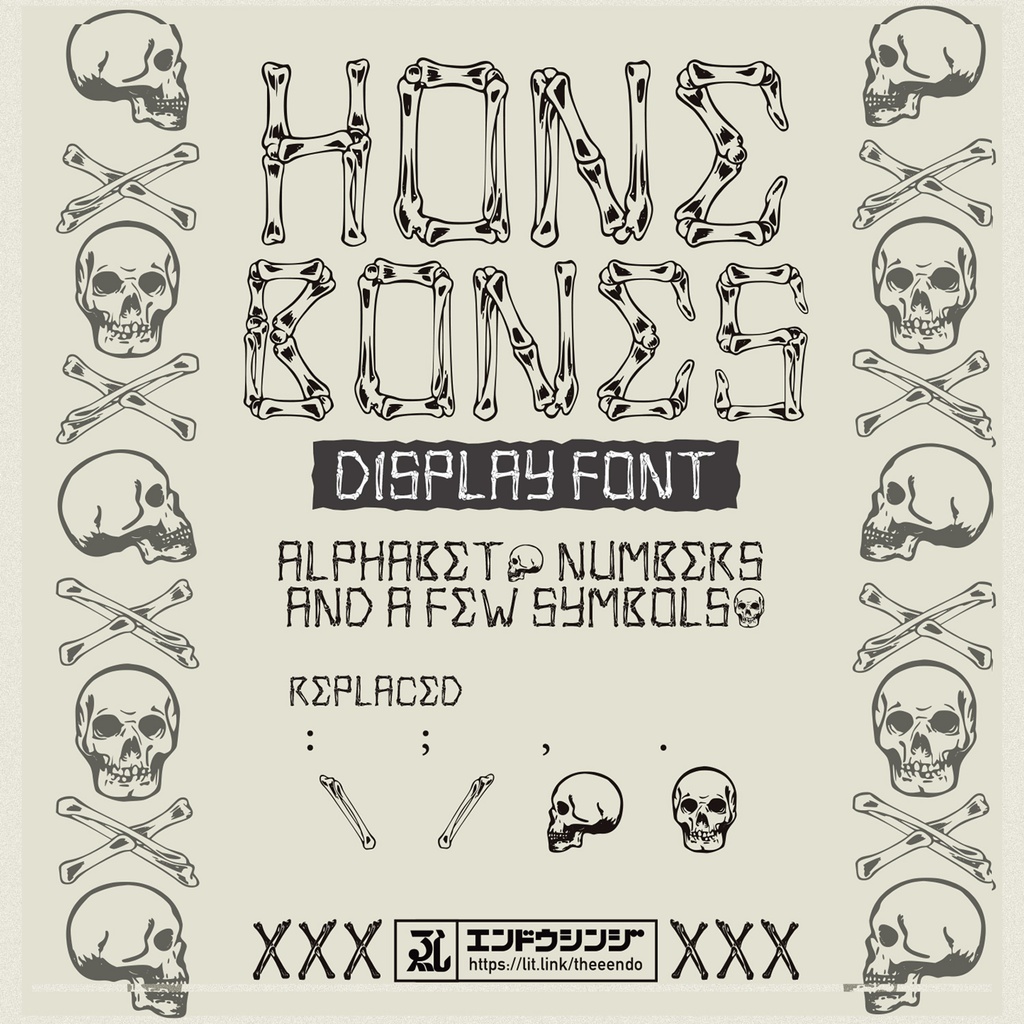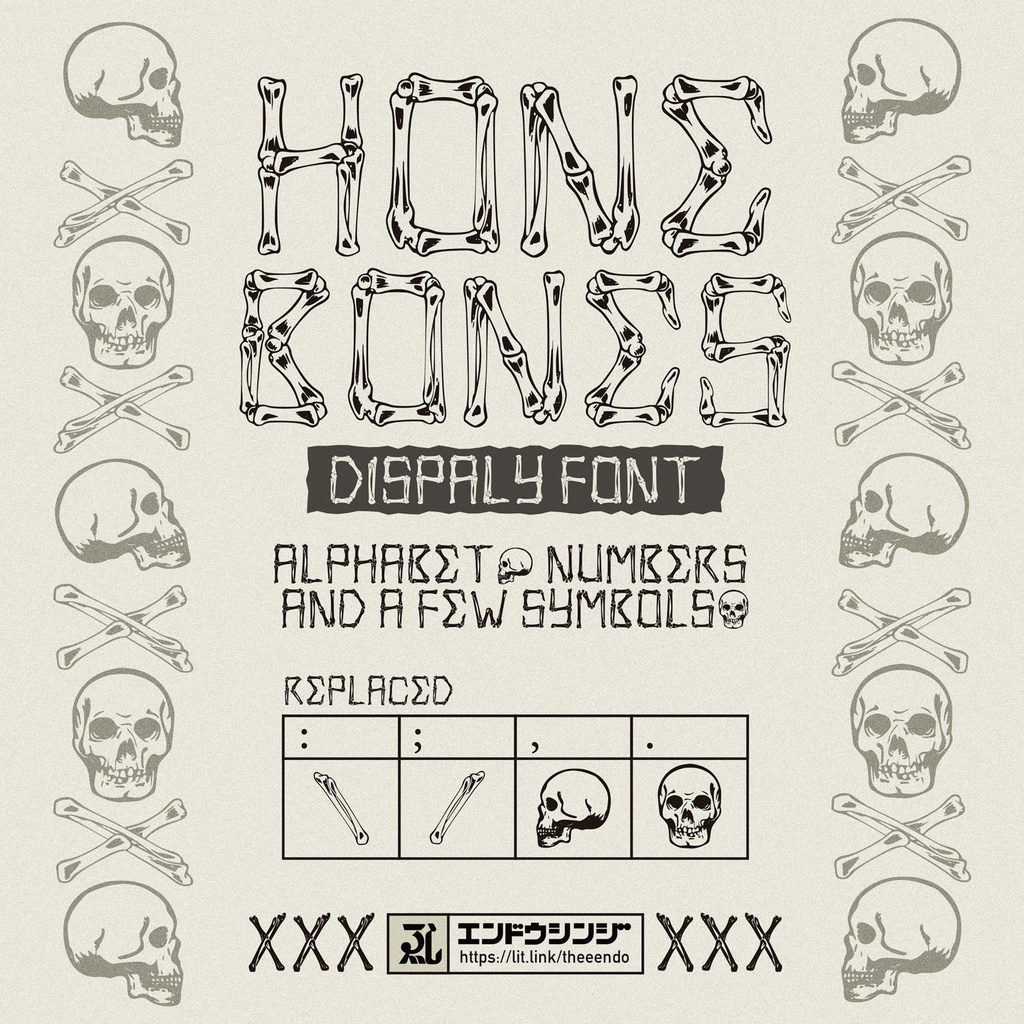
【Free Font】HONE BONES
手描きの骨をベースにしたフォント『HONE BONES』 ■収録文字 英数字・一部記号 66文字収録 OpenTypeフォント *記号「:」「;」「.」「,」はイラストに置き換えられています。 ■ご利用に関して エンドウシンジSNSアカウントをフォローしている方であれば、禁止事項に抵触しない範囲内で自由に使用することができます。商用利用も可です。 フォローされていない方は個人利用の範囲での使用に留めて下さい。 ーーー以下いずれかフォローをお願いしますーーー X : https://twitter.com/mamezone Booth: https://theeendo.booth.pm/ Instagram : https://www.instagram.com/shin_thee_endo/ ■禁止事項 1. 本フォントを第三者に譲渡・貸与・配布・販売することはできません。 2. 本フォントを犯罪行為と見做されるもの、誹謗・中傷目的で使用することはできません。 3. 本フォントを使用したロゴマーク等の商標登録・意匠登録することはできません。 4. 本フォントのデータを元に、新たな類似または同一フォントのデータを作成することはできません。 判断が難しい場合はお問い合わせください。 ■その他 ・本フォントに伴う技術的なサポートはいたしません。 ・本フォントを使用して発生したと思われる如何なる問題についても、Thee endo /エンドウシンジは責任を負わないものとします。 ・動作確認はMacだけで行っています。 ・本フォントの著作権その他一切の権利はThee endo /エンドウシンジ に帰属します。 ・サーバーへのアップロードやゲームソフトへの組み込みも可、その場合は第三者からフォントデータを抜き出し利用できないように保護または暗号化してください。 ・上記に記載されていない条項に関しては、著作権法及び関連法規に従うものとします。 ・本フォントは将来予告なしにアップデート、配布終了する場合があります。 ■お問い合わせ先 mail: mame777@gmail.com X: @mamezone